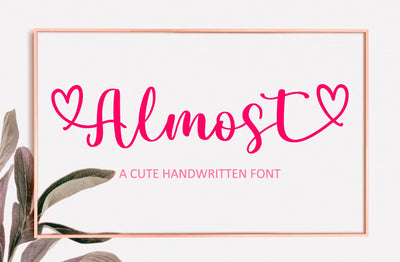
Almost - A cute handwritten font
Hampir adalah font tulisan tangan yang manis dan imut. Jatuh cinta dengan gayanya yang sangat serbaguna dan gunakan untuk membuat undangan pernikahan yang cantik, seni stasioner yang indah, postingan media sosial yang menarik, dan banyak lagi!